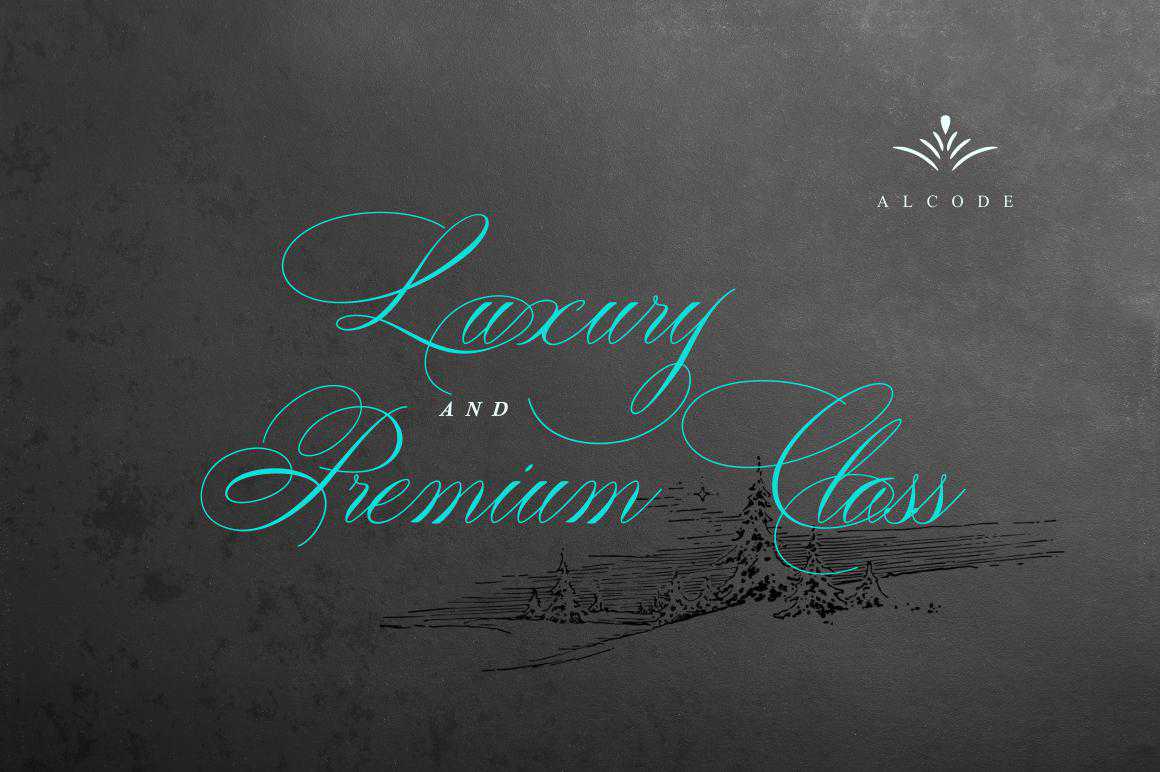
Peachesaclassiccalligraphic字体。这是一款有着独特风格的经典字体。您可以在这里获得一款完美的经典字体。我确信,这款字体会让您的Rich看起来优雅、甜美、完美。Peachesaclassiccalligraphic字体。这是一款有着独特风格的经典字体。您可以在这里获得一款完美的经典字体。我确信,这款字体会让您的Rich看起来优雅、甜美、完美。